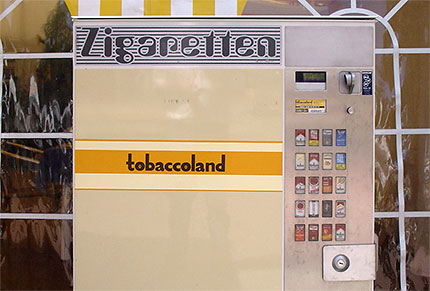
Ein paar Tipps fürs Abendessen
Wie wäre es mit »Vollgestopftes Hühnchen« oder »Feige Mischgemüsekasserolle«? Als Dessert empfehle ich »Zertrampelte Quitte«, »Enträtselte Schweiß-Geback« und diese automatisch übersetzte Rezeptseite: Türkische Küche ...
Verdrehte Worte
John Langdon, der Autor des Buches »Wordplay«, ist Experte für Ambigramme, also sind symmetrische Symbole oder Schriftzüge: Gedreht oder gespiegelt bleiben Form und Lesbarkeit erhalten. Ambigramme spielen eine große Rolle im Roman Illuminati von Dan Brown.
Die Entwerfer lesbarer Ambigramme bedienen sich eines Tricks: Sie konstruieren Buchstaben, die um 180° gedreht einen anderen Buchstaben ergeben. Das funktioniert ziemlich gut mit Schreibschriften und gebrochenen Schriften, weil unser Auge diese – schwer lesbaren Formen – mit viel Toleranz interpretiert. Das können inzwischen auch Maschinen, wie dieser Ambigramm-Generator, mit dem ich das obige Fontblog-Logo erzeugt habe. Versucht es selbst mit eurem eigenen Namen ...
Ambigramme aus Sans-Serif- oder Serifen-Schriften zu generieren ist eine eher knifflige Aufgabe, wie die Galerie von Langdon beweist. Auf dieser Seite erläutert er den Unterschied zwischen symmetrischen und asymmetrischen Ambigrammen. Richtig gemein können die asymmetrischen Wörter sein, wenn sie plötzlich die gegensätzliche Bedeutung annehmen. Also: Nie handgeschrieben Verträge unterschreiben, immer auf getippte oder gesetzte Texte bestehen.
Lost in Dallas ...
Mein alter Kumpel Jan Chipchase – er ist Brite, arbeitet für Nokia, in Tokio, und reist ununterbrochen in der Welt herum (war Sprecher auf der TYPO 2002) – führt ein Online-Tagebuch (Fundgrube!), das sich mehr und mehr zum Leitsystem-Blog entwickelt. Dabei liefert er keine Antworten, sonder er stellt (fotografische) Fragen.
Das obere Foto vom Flughafen Dallas taufte er »Zusammenhang versus Redundanz«. Sicher könnte man aus den vier Zeilen eine machen, aber warum der englischsprachige Hinweis zweimal auftaucht ... kulturelle Gründe?
Dieses Foto (immer noch Dallas) überschreibt Jan mit »Context & Unintended Understanding«, was ich mal nicht übersetze, weil mir schon die Übersetzung von »Consistency vs. Redundancy« (s. o.) nicht gelungen ist.
Trost von Coca-Cola
Eine Frage der Einstellung. Die haben gute Texter, bei ... wie immer die Agentur heißt. Siehe auch: Eben, auf der Fanmeile. Quelle: zillionhours c/o flickr
Wenn bald der letzte Zigaretten-Automat ...
Mit welcher Schrift gestaltet ihr gerade was?
Robert Schöne hat es vorgeschlagen, und seine Wünsche waren mir bisher immer Befehl(e): Mit welcher Schrift gestaltest Du gerade welches Dokument? Mitte im Kommentar eintragen, erst mal ohne Abbildung (kommt vielleicht bei der 2. Befragung). Ich weiß jetzt schon, dass es nicht mehr als 10 Teilnehmer geben wird. Wie Cameron Moll das mit den 174 Feedbacks hin gekriegt hat, ist mir ein Rätsel.
Der neue Freizeitspaß: Zidane-Pogo
Wir haben Zinédine Zidane Unrecht getan, mit unserem schnellen Urteil. Die Fifa denkt darüber nach, den Italienern den WM-Titel wegen verbaler Beleidigung wegzunehmen (was nichts anderes heißt, als Zidane zu rehabilitieren) ... andere fühlten sich an den Tanzstil der Punk-Szene erinnert: die Pogo-Variante Slamdance. Das Salzburger Designbüro Brainpool-Media wirbt mit einem Video für den Zidane-Pogo als Problemlöser.
WM-2010-Logo ... Achtung, Satire!
Zidane: falsch programmiert
Photoshop-Spielerei: Fontblog
Die Mutter aller Designwettbewerbe
Zeugwart Manfred Drexler ist schuld
Der verflixte Spickzettel (Simulation, Schrift FF Justlefthand)
Wir erinnern uns: Kurz vorm Elfmeterschießen im Viertelfinalspiel Deutschland – Argentinien reichte Jürgen Klinsmann unserem Torwart einen Zettel, den er las und anschließend in seinem linken Schuh versteckte. Da blieb er dann auch drin, bis zum gestrigen Halbfinalspiel: der Zeugwart der Fußball Nationalmannschaft, Manfred Drexler, hatte ihn beim Schuheputzen übersehen. Als Lehmann zur Verlängerung sein zweites Paar anzog – das mit dem Spickzettel – fiel ihm der obige (längst ungültige) Hinweis in die Hand, den er befolgte.
Die WM-Spaß-Songs für heute Abend
Elf kleine Italiener (Kaya, Delta Radio)
Arrivederci Italien ... (Ringo & Ingo, Radio RSH)
Podolski, er wird uns ins Finale schießen (Anonymus, Radio SAW)
MamaMia Italia (Anonymus, Atomofen)
Trivia (4): Ball muss neu beschriftet werden
Meine Prognose vom Freitag bedarf einer Revision.
Verwendete Schrift: Trivia; Made by FontShop und nur dort kostenlos im Download ...
Trivia (3): Wallpaper »Hemd auszieh’n!«
Wer widerspricht?
Vielleicht hat es mit der handwerklichen Herkunft des Formulierung zu tun. So wie man Statuen aus Marmor fertigt, so hat man im Bleisatz Texte aus der Garamond gesetzt.
Für uns Digitalkinder ist Schrift zur virtuellen Masse geworden, so wie Farben und Töne: ein Buchumschlag in blau oder eine Symphonie in C-Dur. Also: gesetzt in Garamond.
Wer widerspricht?